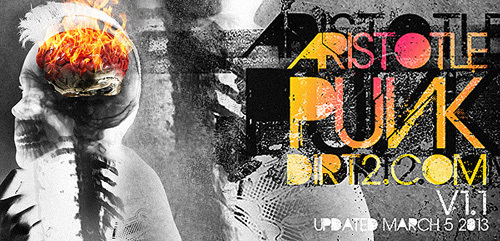
Aristotle Punk od Dirt2.com - SickCapital to darmowy, poobijany font typu punk caps, zbudowany z surowych, geometrycznych form i agresywnie przetartych powierzchni. Ciężkie litery są poprzecinane zadrapaniami, odpryskami i smugami, a ostre, ukośne cięcia tworzą kolażowy, konfrontacyjny rytm.
Pasuje idealnie do plakatów koncertowych, okładek płyt, zinów, grafik streetwearowych, ulotek protestacyjnych i nagłówków, które wymagają efektu zniszczonej odbitki z drukarni. Użyj tego darmowego fontu do krótkich tytułów lub haseł, gdzie szerokie kształty spajają kompozycję, a jednocześnie wyeksponowana jest surowa tekstura.